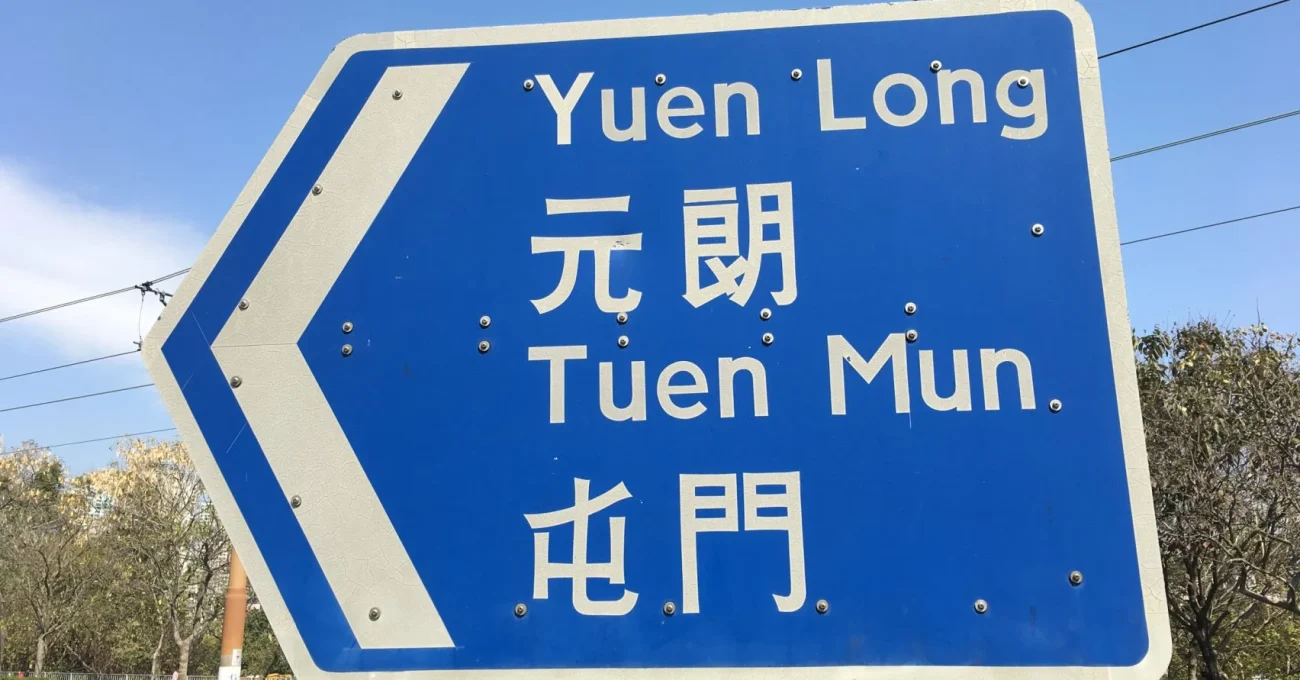
Sivil toplum kuruluşu Road Research Society, şehrin görsel kültürel mirasını koruma projesinin bir parçası olarak Hong Kong’daki eski yol işaretlerini dijitalleştirdi ve Prison Gothic adlı yeni bir yazı fontu yarattı.
Prison Gothic’i yaratmak için şehirdeki eski sokak tabelalarını tarayan dernek çalışanları, her bir işareti fotoğrafladı. Ardından görüntüleri yazı fontu tasarım yazılımı olan Glyphs’e aktardı. Ekip, yazılımı kullanarak işaretlerin değişen çizgi kalınlıkları gibi özgün özelliklerini tek tip ve modern bir yazı tipine dönüştürdü. Şimdiye kadar yaygın olarak kullanılan 8 bin Çince karakter içeren yeni yazı tipi, şehrin sokaklarındaki yol levhalarından toplanan 600 karaktere göre modellendi.
Sans serif ailesine mensup olan yeni font, esasında hayli uzun uğraşlardan sonra ortaya çıktı. 2016 yılında başlayan eski yol işaretlerinin dijital yazıya dönüşüm projesi, Çin hükümetinin yol tabelalarında yaptığı değişiklikler nedeniyle zaman zaman kesintiye uğradı.
1970’lerden beri yol levhalarının tamamının mahkûmlar tarafından el yapımı olarak hazırlandığı Hong Kong’da, yeni fontun adı bu nedenle Prison Gothic olarak belirlendi.
Dernek yetkilileri aynı zamanda, insanların Prison Gothic’i normal bir yazı fontu gibi kullanabilmesi için yol levhalarının dışında ek karakterler yaratmaya karar verdi. Ancak en büyük zorluk, karakter setini Çince gibi karmaşık ve zor bir dilde en çok kullanılan kelimelerin yüzde 98’ini kapsayacak şekilde genişletmek.
Hong Kong modern tasarımların yol tabelalarına dönüştüğü ilk yer değil. Daha önce Hollandalı tasarım stüdyosu Studio Dumbar’ın Güney Kore ekibi, ülkedeki ulusal yol tabela sistemi için yeni bir yazı tipi yaratmıştı. Ülkemizde de İzmir’in markalaşması kapsamında İzmir Vakfı tarafından yürütülen bir proje ile şehre özel İzmir Fontu tasarlanmıştı.